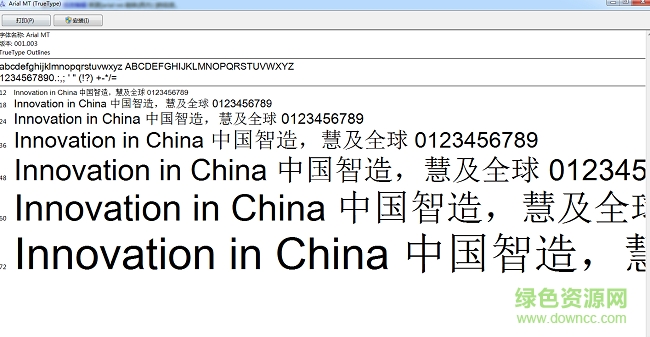
arial mt-粗體(西方)
arialmt字體是一款可讀性強的英文無襯線字體,這款字體線條平實,端正大氣,筆畫粗細變化不太明顯,標題正文都可以使用,屬于不容易出錯的字體類型,歡迎大家免費下載!
arial字體介紹
Arial其實是Monotype Grotesque系列的變種。設(shè)計Arial時考慮到會在電腦上面使用,在字體及字距上都作了一些細微的調(diào)整和變動,以增加它在電腦屏幕上不同分辨率下的可讀性。
英文字體分類
字體可以分為襯線體(serif)和無襯線體(sans serif)兩類。比如常見的TimesNew Roman字體就是一種襯線字體,Arial字體就是一種無襯線字體。